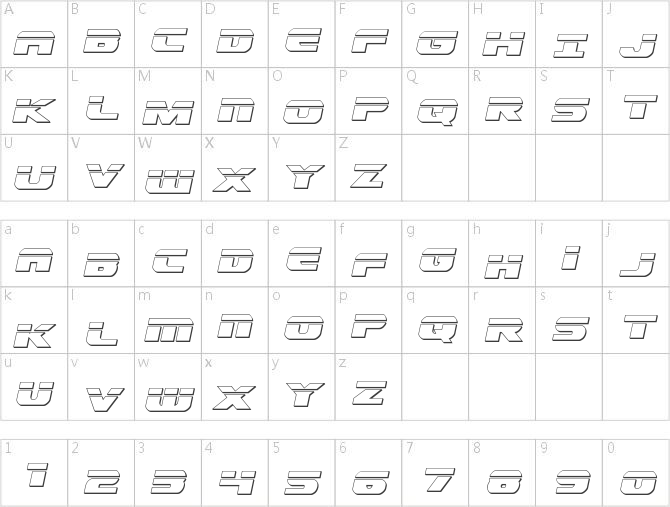
Dekaranger Bullet Italic
Dekaranger Bullet Italic字體字庫是一款讓人賞心悅目、百看不厭的英文字體,適合各類廣告和產(chǎn)品包裝設(shè)計應(yīng)用,字體大小0.05MB,格式為ttf字體,上傳用戶是得·岸,作者/版權(quán)方為未知